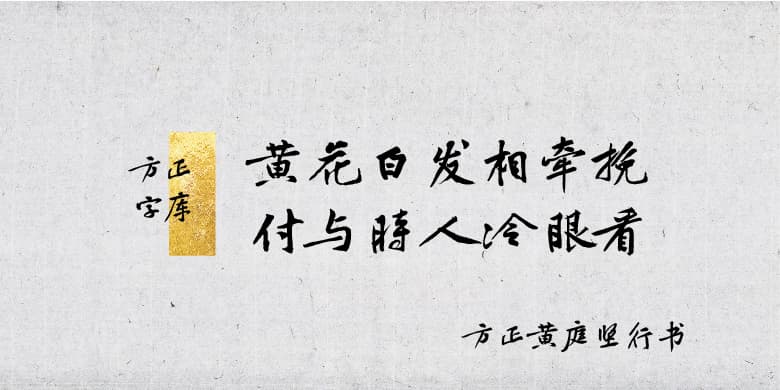
品牌:方正字库中华精品字库设计师:过中运,王文娜发行时间:2020字库编码:简繁扩展(GBK)分类:常规书写·毛笔字体属性:精品字
·字体特征
以《松风阁诗帖》为开发依据。这款行书壁画虬曲有度,中宫紧缩并呈放射状,结体跌宕开阖,呈现出奇崛瘦硬的面貌,气质自由奔放。
·关于黄庭坚
黄庭坚(1045-1105)字鲁直,号山谷道人,洪州分宁(今江西修水)人。自幼勤奋好学,博览经史百家。宋英宗治平四年(1067)进士。神宗朝曾任叶县尉、北京(今河北大名东)国子监教授、太和知县等。黄庭坚是“苏门四学士”之首,也是北宋后期的著名文学家。他论诗标榜杜甫,提倡“无一字无来处”、“点铁成金”。诗作多写个人日常生活,讲究修辞造句,追求奇拗瘦硬的风格,是“江西诗派”的鼻祖。也善为词,其中表现谪居生活、兀傲性格、离别亲情、塞垣风光、守边壮志的部分作品,疏宕洒脱,豪迈奔放。黄庭坚还是一位著名书法家,有《山谷集》《山谷琴趣外篇》,存诗一百九十首。
设计师:过中运、王文娜